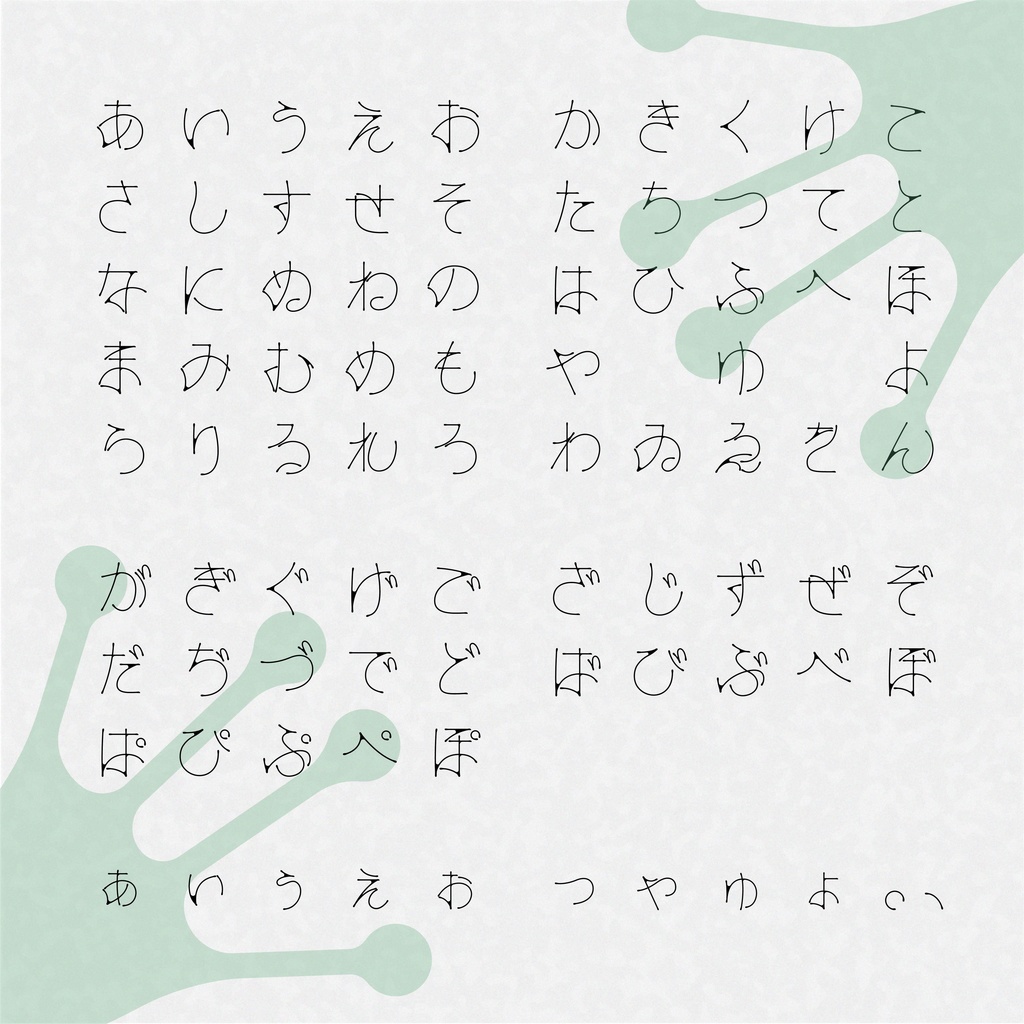
すいれん フォント
睡蓮の葉から着想を得たひらがなフォントです。 フォント名は ” すいれん ” だけど、文字に隠れているのは “ カエルの手 “ しっとりとした柔らかい丸みのある文字をしています。 タイトルやコピー、短文などにお使いください。 【収録文字】 ・全角ひらがな(濁音・半濁音・小文字も収録されています) ・全角記号(句点・読点のみ) 【利用規約】 ・当フォントをダウンロードした自転で利用規約に同意したものとみなします。 ・商用・非商用を問わず利用可能です。 -使用報告は不要ですが、していただけると喜びます。 Twitter : https://twitter.com/kt__0728 ・作者は著作権は放棄していませんので、自作発言はご遠慮ください。 ・当フォントを利用して起こった、いかなる損害に対しても作者は責任を負いません。 【禁止事項】 ・フォントファイルの改変・無断転載・再配布・販売 ・当フォントを利用した制作物、ロゴなどの商標登録 【注意事項】 ・ダウンロードデータには利用規約、.ttfデータ(Suiren / Suiren_other)2つが収録されています。 濁音・半濁音を含む「あ〜ん」はSuirenに収録されており、「ぁ〜ぉ」「ゐゑ」「、。」はSuiren_otherに収録されております。ご了承ください。